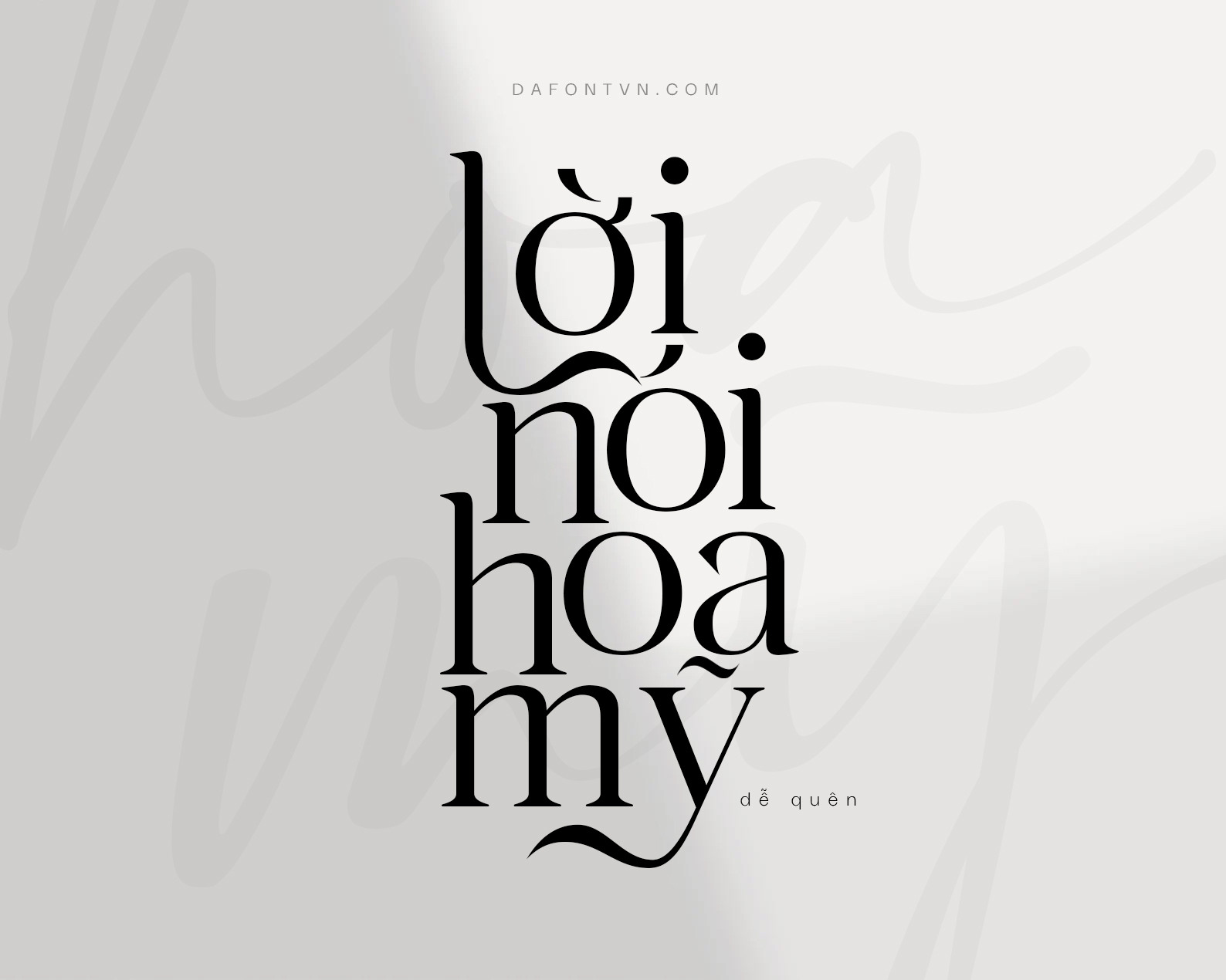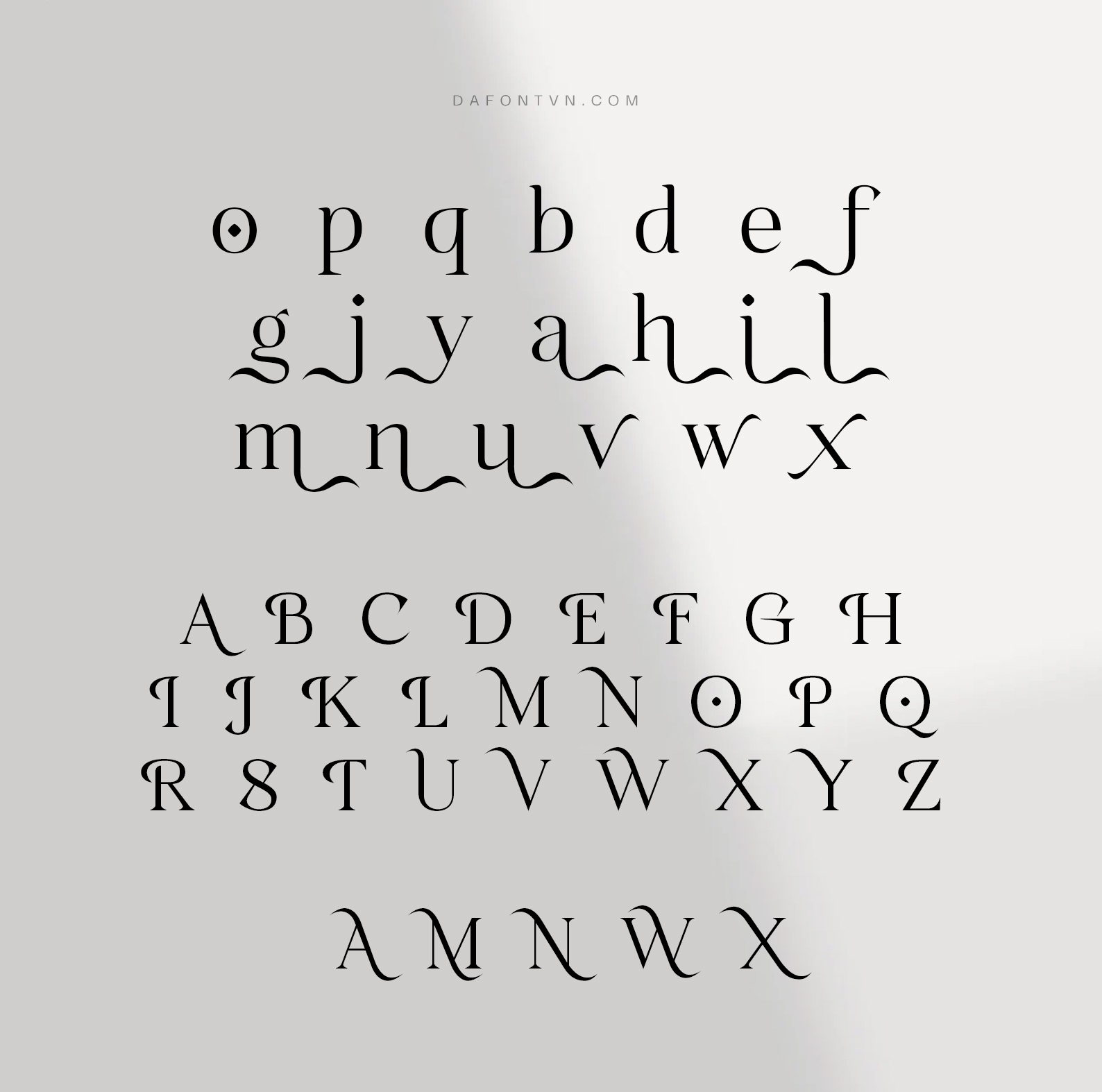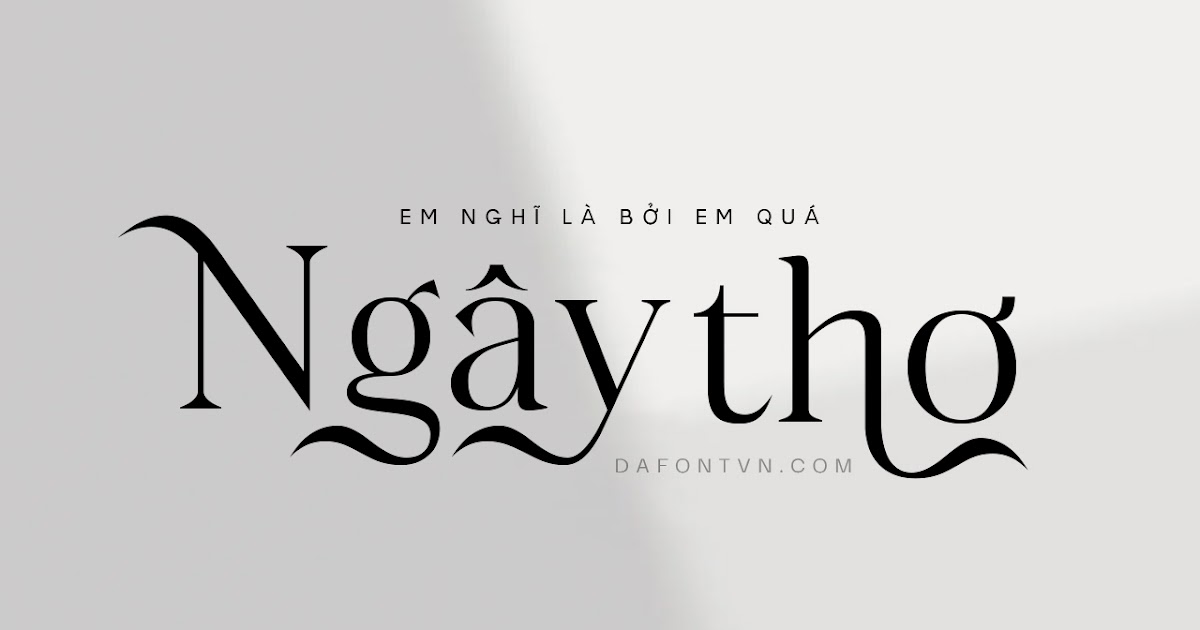
Font Mighty Wings Việt hóa – Serif hiển thị sang trọng
Mighty Wings Font – 1 kiểu serif hiện đại, sang trọng và vẻ đẹp quyến rũ.
Font Mighty Wings Việt hóa lấy cảm hứng từ những tác phẩm thiết kế hiện đại đi kèm với một số alternate và ligature. Bạn có thể kết hợp để tạo ra các tác phẩm hoàn hảo. Bạn có thể sử dụng font chữ này cho nhiều các thiết kế như thiết kế biên tập, tạp chí, thương hiệu mỹ phẩm, quảng cáo thời trang, cửa hàng, văn phòng, thiết kế blog, thiết kế quảng cáo, thiệp mời, tiêu đề sách / trang bìa, typography…
Font được chỉnh sửa lại hoàn toàn so với font gốc, các dấu, ký tự được làm mới lại để font trở nên đẹp mắt dễ sử dụng hơn. Tất nhiên là chúng tớ đã việt hóa và kering đầy đủ, mã hóa PUA và tối ưu hóa để bạn dễ dàng sử dụng trên bất kỳ phần mềm nào.